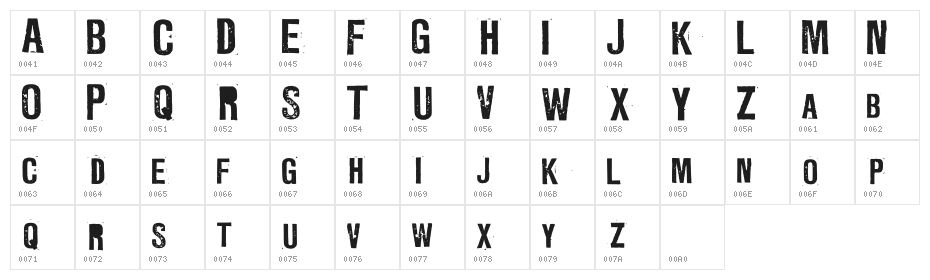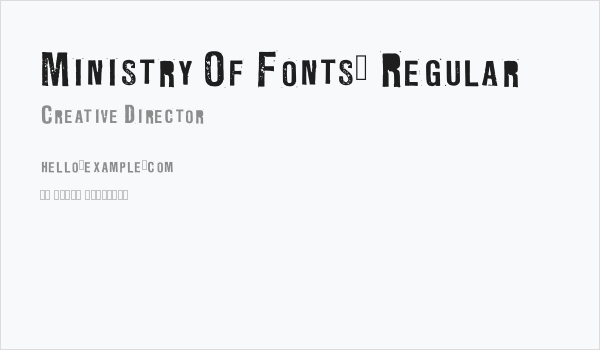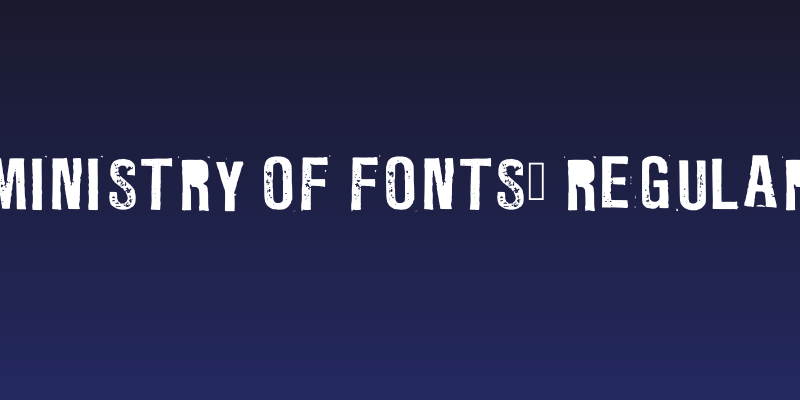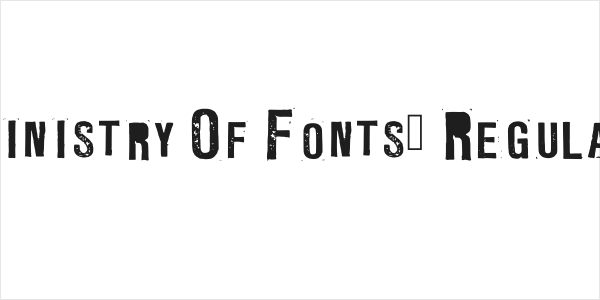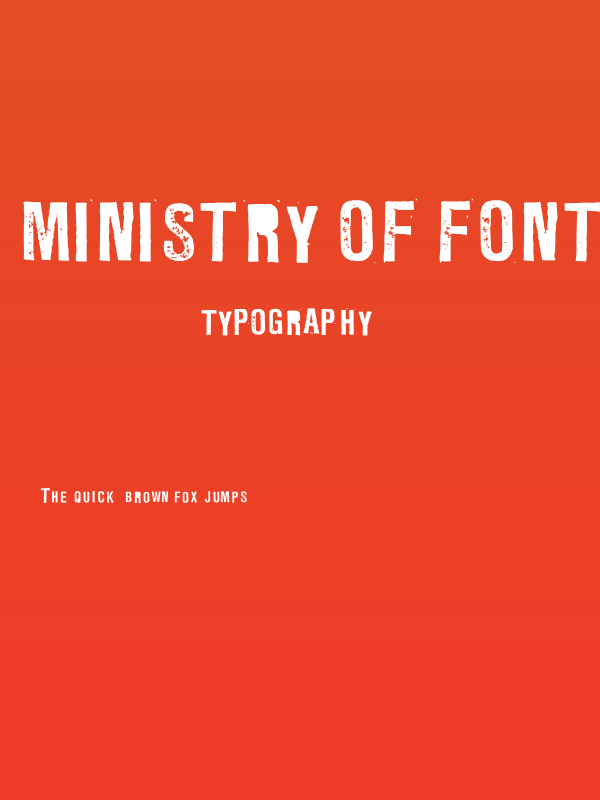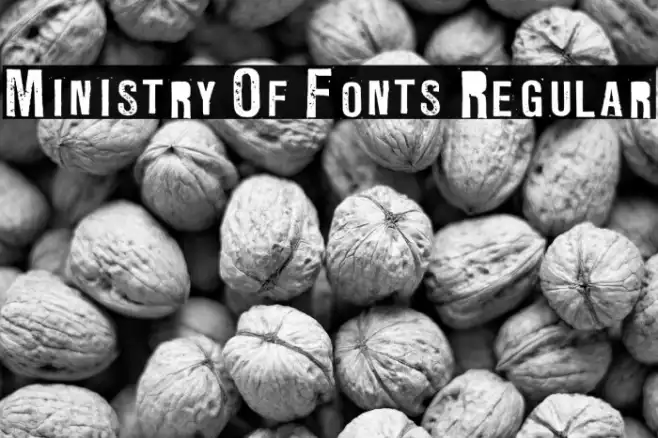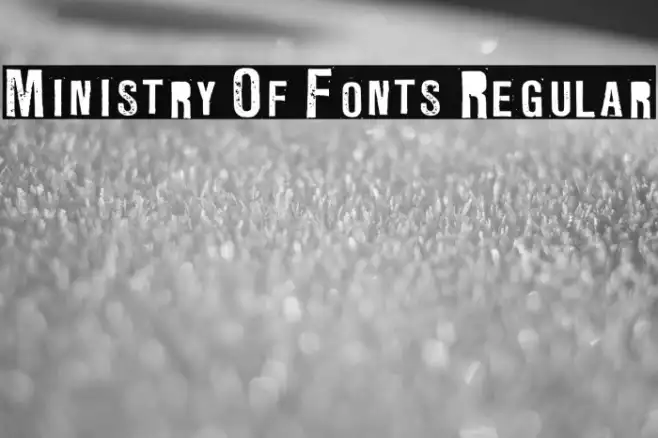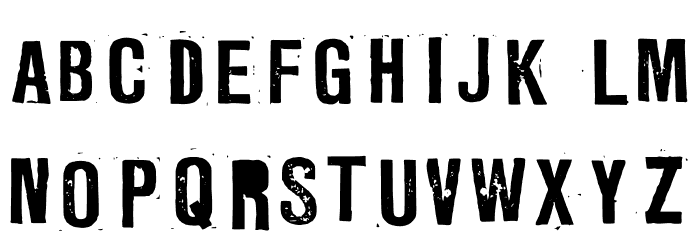
Ministry Of Fonts3 Regular Font
✎ Typewriter
| Kategorien | Typewriter |
| Gesamtstil | Vintage |
| Vorgeschlagene Projekte | Ideal for posters, album covers, branding for vintage-themed products, or any design needing a rustic, edgy touch. |